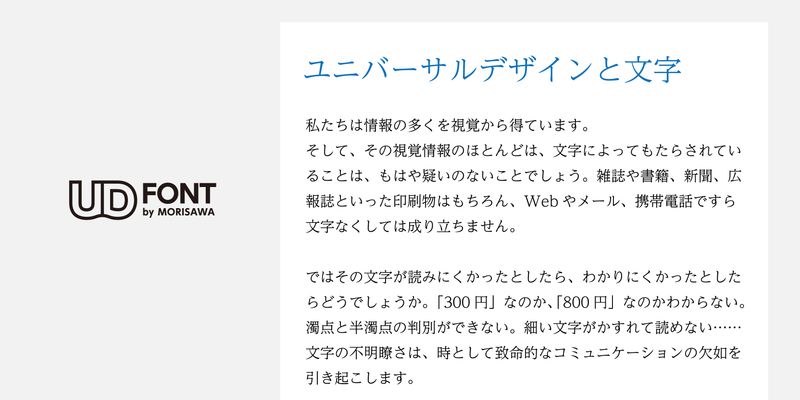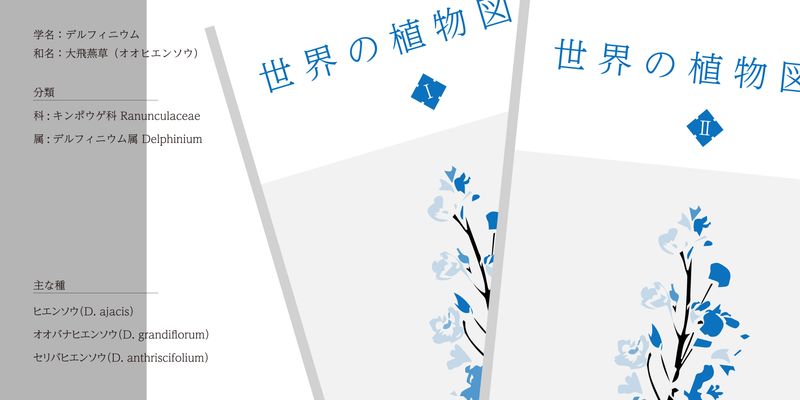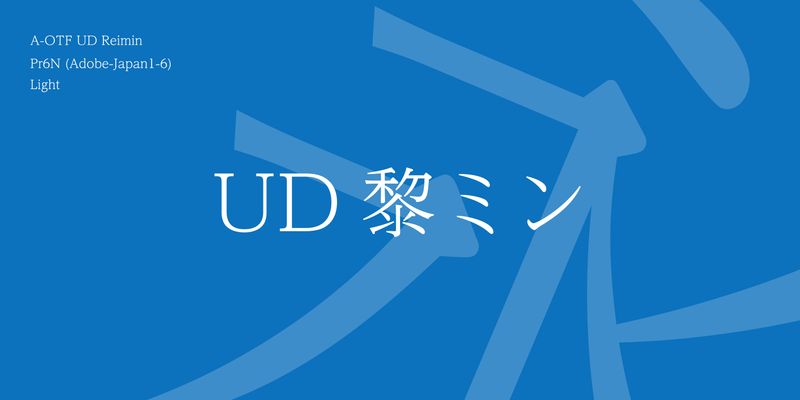
UD Reimin ist eine universelle Design-Schrift, die entwickelt wurde, um die Benutzerfreundlichkeit zu erhöhen, indem den für die Mincho-Serifen typischen horizontalen Strichen ein solides Gewicht hinzugefügt wurde. Die Kana hat ein modernes Design, das sich durch größere Ziffern und geringeren Kontrast auszeichnet. Das lateinische Alphabet und die Ziffern sind klar und gut lesbar. Die Schrift ist sowohl vertikal als auch horizontal wunderschön ausgerichtet.